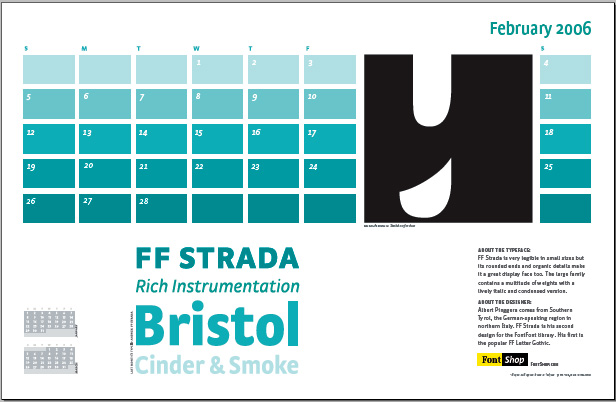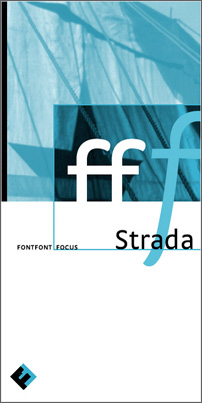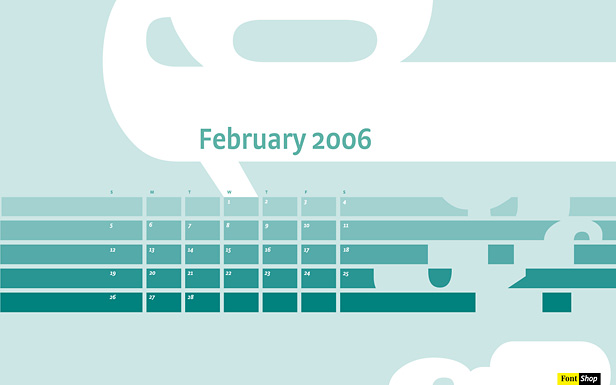
Februar-Blatt, gestaltet in der FF Strada von Albert Pinggera ... sieben
ein kleiner Hinweis, welche Schrift uns im kommenden Monat erfreuen wird. Weiterlesen ...
Für die Gestaltung des Januar-Kalenderblattes griffen unsere Gestalter
zur Schrift FF Strada aus der FontFont-Bibliothek. Albert Pinggera entwarf die
ersten Schnitte dieser Schrift noch während seines Studiums in Den Haag.
Als Ausgangsbasis dienten ihm in Stein gemeißelte Kurven, aus denen er
zunächst den kursiven Schnitt herleitete. In den darauf folgenden Jahren
entstand eine sehr gut lesbare Sans Serif mit geringem Kontrast und
außergewöhnlichen Formen in den Display-Größen. FF Strada
wurde 2003 vom Type Directors Club ausgezeichnet. Mehr über die Schrift in
einer kostenlosen FontFont-Focus-Broschüre.*